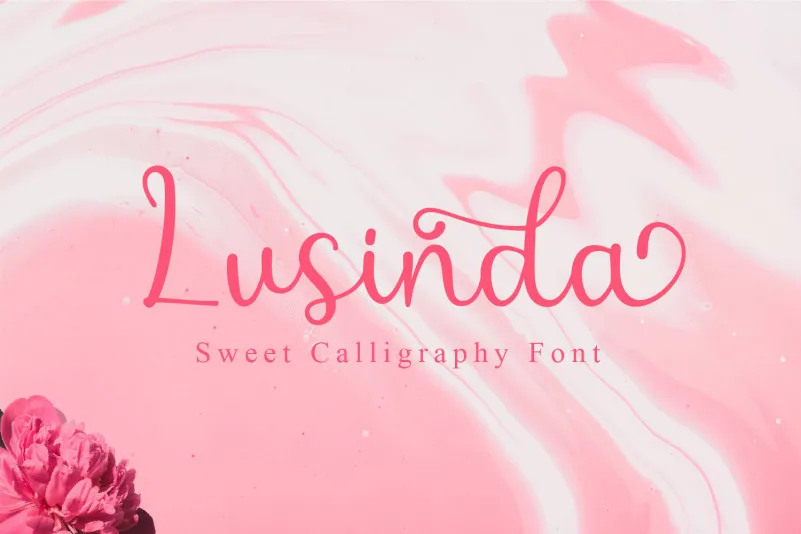
Lusinda – Feminine Font – Download Grátis
A fonte ‘Lusinda – Feminine Font’ é uma elegante escolha para qualquer projeto de design que procure dar um toque sofisticado e delicado. Inspirada no estilo do calligrafia, ela se destaca por sua leveza e sutileza, com linhas suaves e arredondadas. Este font traz um toque alegre ao seu trabalho, onde cada caractere parece dançar perto da linha de base. Através desta fonte, você pode dar um tom refinado e feminino à sua página web, logomarca ou qualquer outro projeto gráfico que esteja em desenvolvimento. Com ‘Lusinda – Feminine Font’, transforme o básico em algo excepcional através do design de letras de alta qualidade.